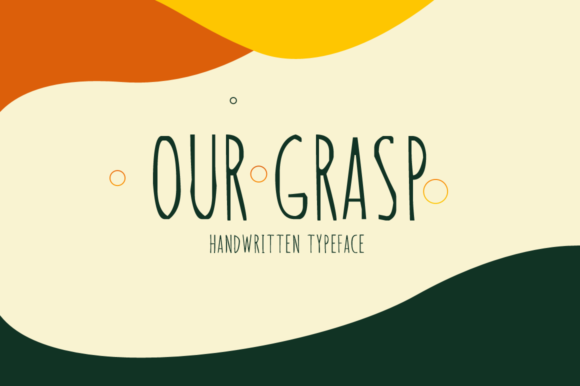
Our Grasp
Jika anda sedang mencari aset berkualiti tinggi seperti Our Grasp, pakej premium ini merupakan pilihan yang hebat untuk projek kreatif anda.
Dicipta dengan ketepatan, Our Grasp menyediakan vektor yang bersih, tipografi yang licin dan lesen komersial untuk ketenangan fikiran.
Sama ada anda mencipta produk POD (Print on Demand), jemputan perkahwinan atau grafik media sosial, Our Grasp amat bersesuaian.